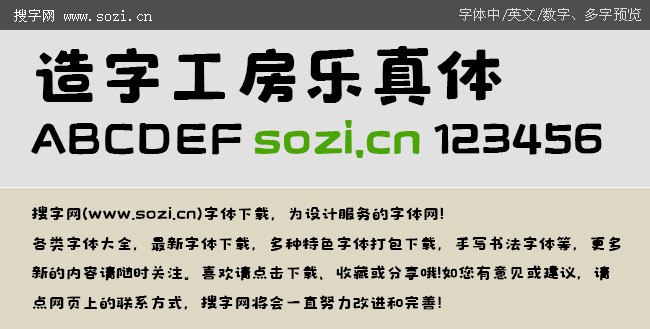
造字工房樂真體
搜字網(wǎng)給大家提供一款造字工房樂真體中文字體下載,造字工房樂真體是一款很可愛的藝術(shù)字體,造字工房樂真體筆觸稚拙,字體組合結(jié)構(gòu)松散、拙中見巧,具有很強(qiáng)的視覺感染力,風(fēng)格詼諧幽默,卡通喜愛。此款字體適用于兒童讀物、報(bào)刊雜志標(biāo)題、廣告設(shè)計(jì)等應(yīng)用。(本字體為個(gè)人非商用版,如需要商用請聯(lián)系官方購買版權(quán))